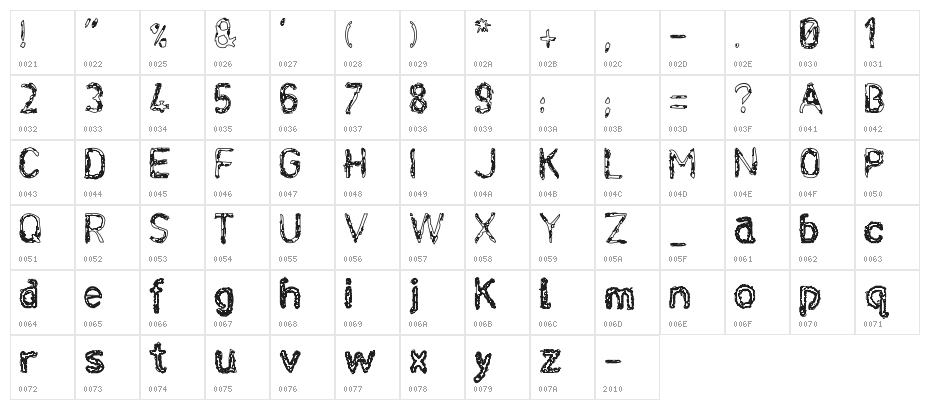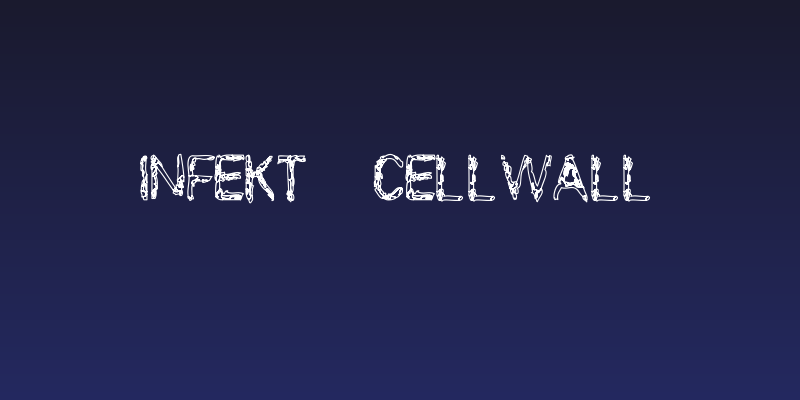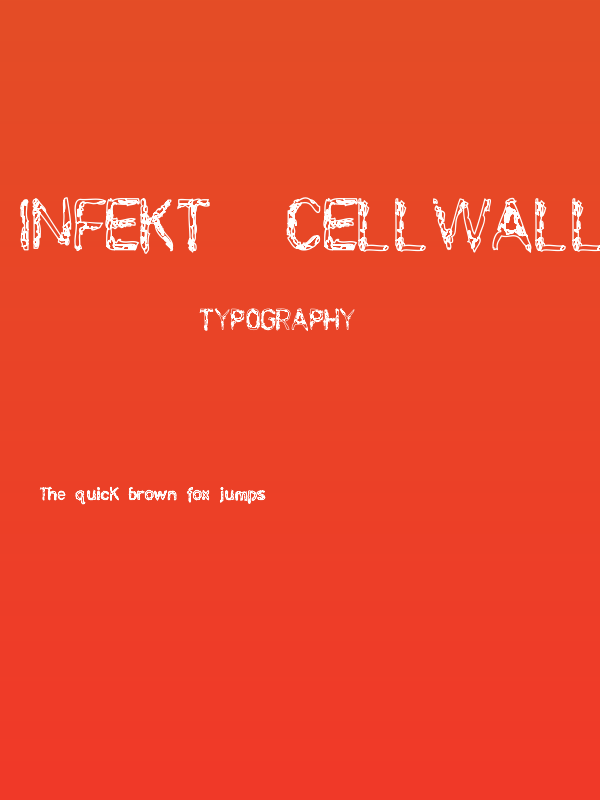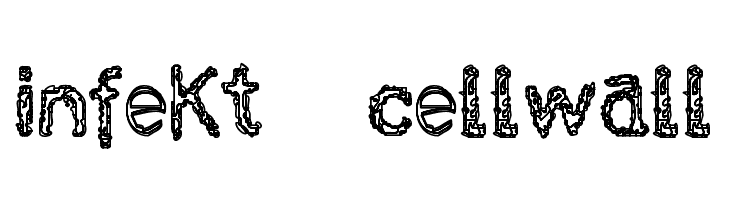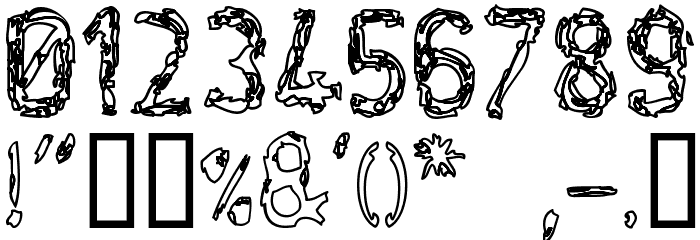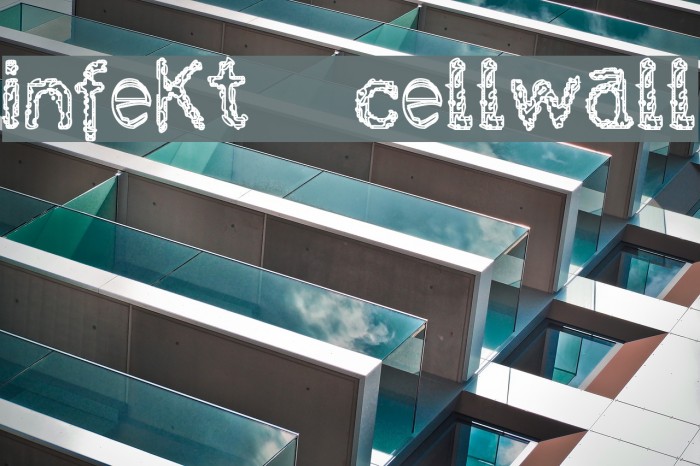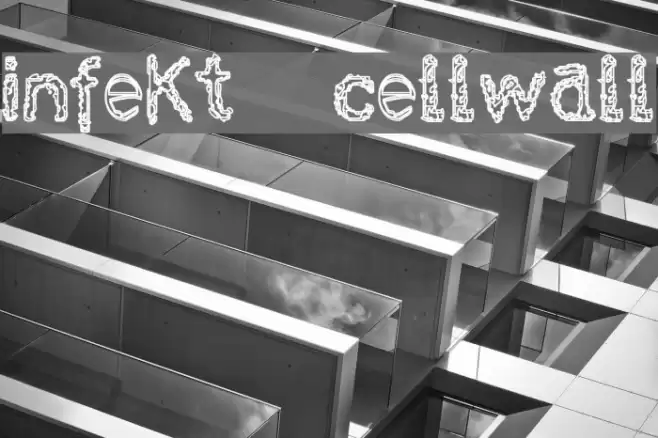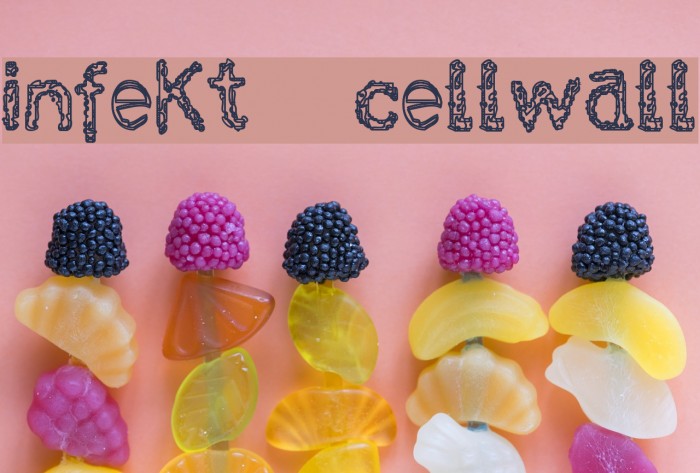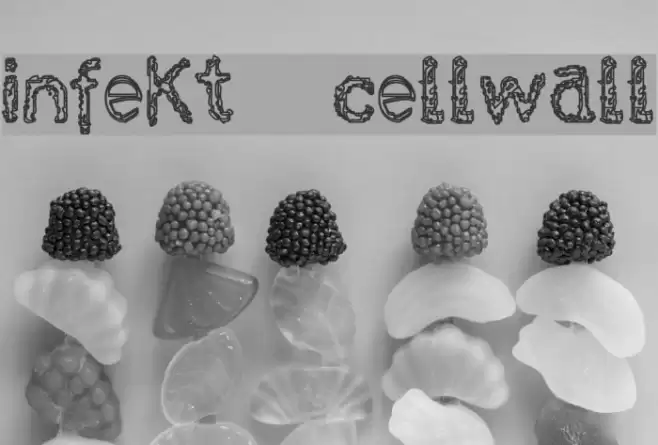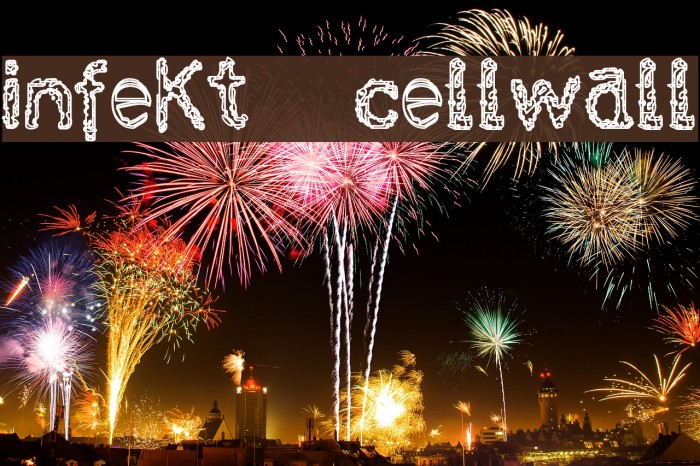
infekt cellwall Font
| Vorgeschlagene Projekte | Ideal for science-themed posters, album covers, or any project requiring a bold, organic aesthetic. |